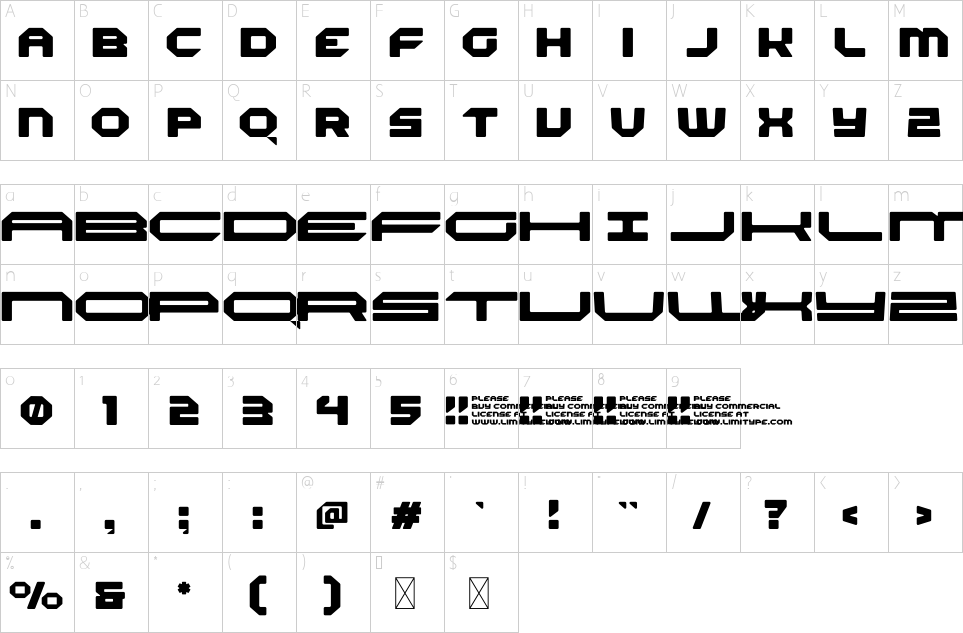
Descubra o equilíbrio entre elegância e versatilidade com a fonte Alphatron. Desenvolvida pela Limitype, esta fonte é perfeita para projetos digitais que buscam uma aparição contemporânea e sofisticada. Com seu design clean e harmonioso, a Alphatron se adapta perfeitamente a um número de formatos de mídia, desde e-books até design gráfico. Se você busca uma fonte moderna e versátil para seus projetos, o Alphatron é uma escolha inteligente. Baixe hoje e inspire-se com sua elegância única.